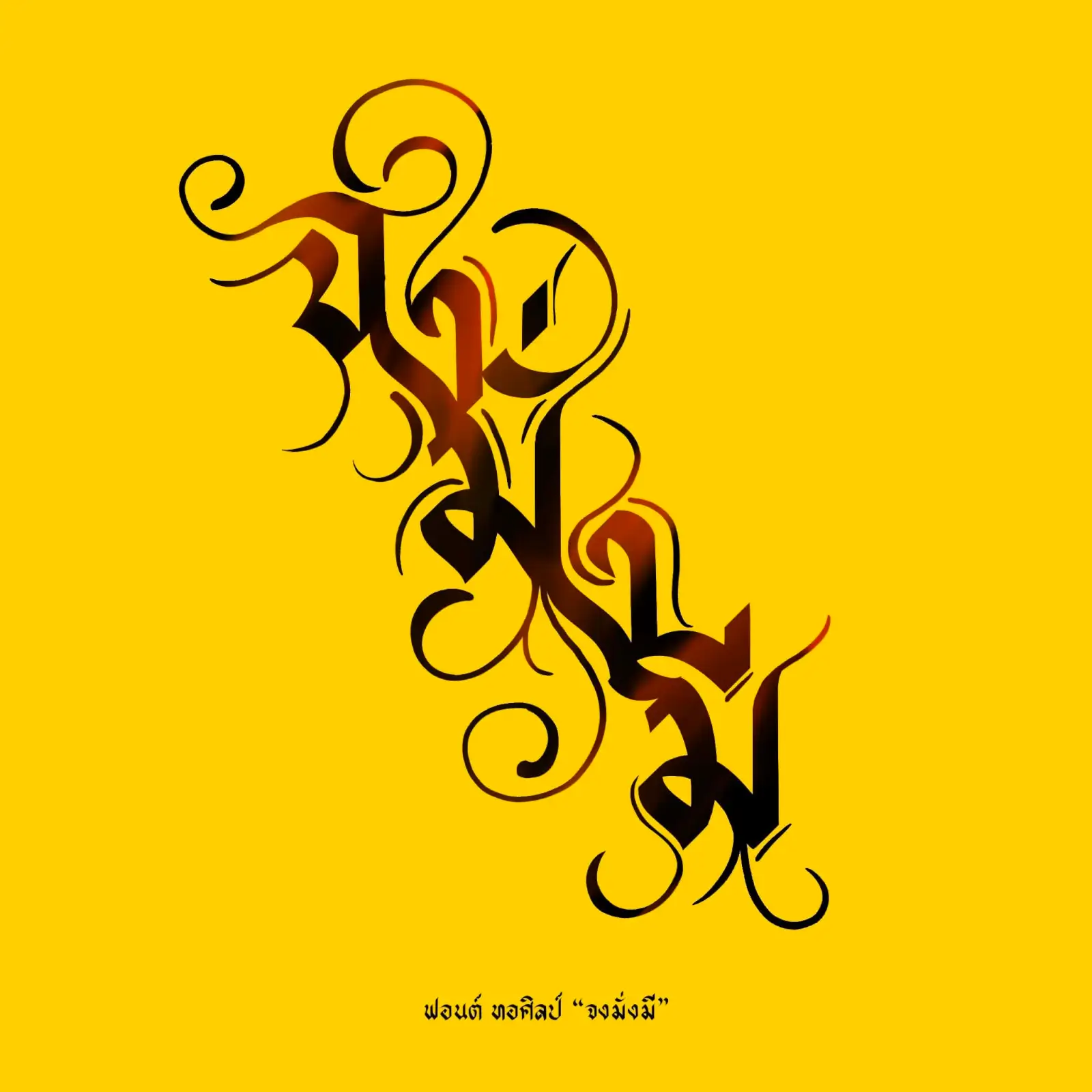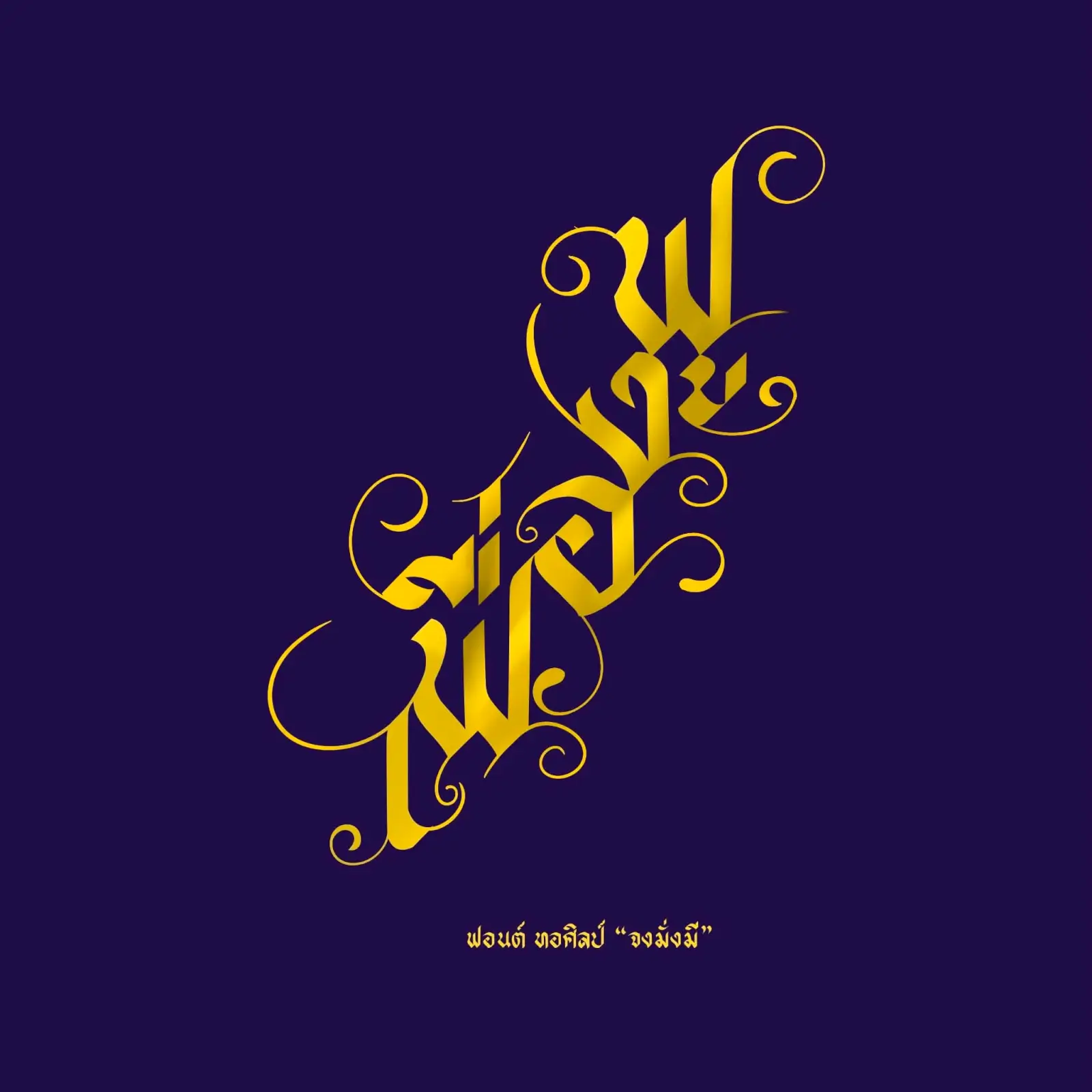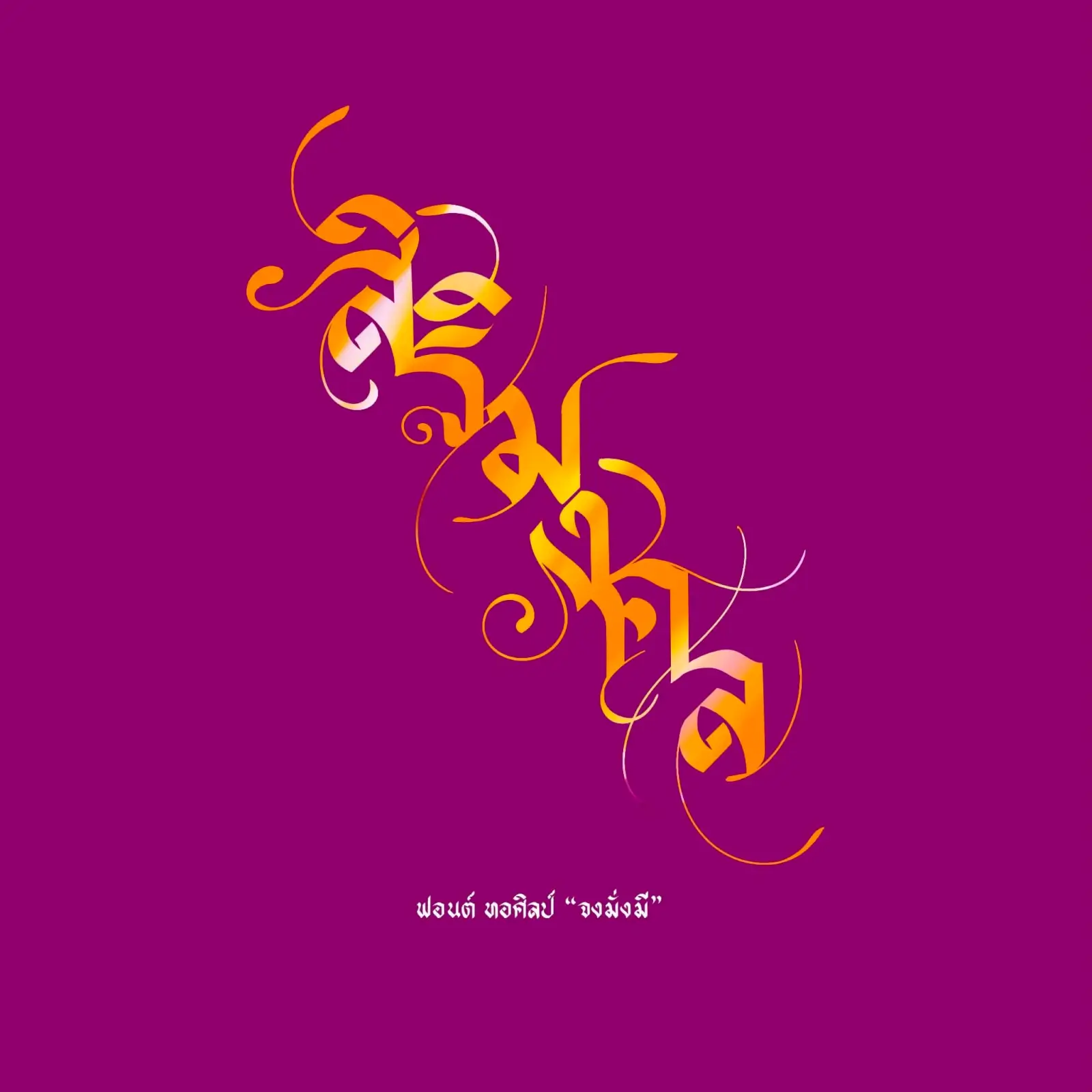
ฟอนต์ริบบิ้นในตระกูลฟอนต์ทอศิลป์อีกตัว ชื่อฟอนต์ “ทอศิลป์ จงมั่งมี” ตั้งใจตั้งชื่อให้ฟังแล้วเป็นมงคล และลองเอาฟอนต์ทอศิลป์ จงมั่งมี มาออกแบบเป็นคำมงคลดูด้วย ออกมาสวยงามมากเลยครับ
ฟอนต์โดย : ระจัน โรงเรียนสอนศิลปะทอศิลป์
ทอศิลป์ จงมั่งมี (Torsilp ChongMangmi)